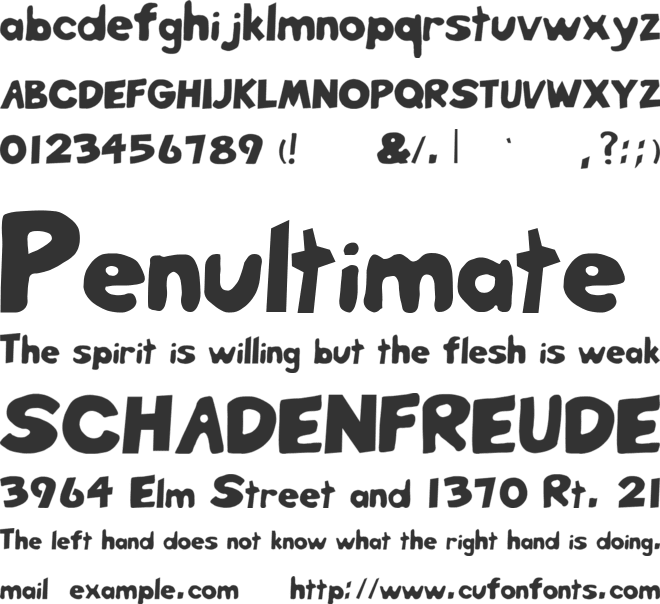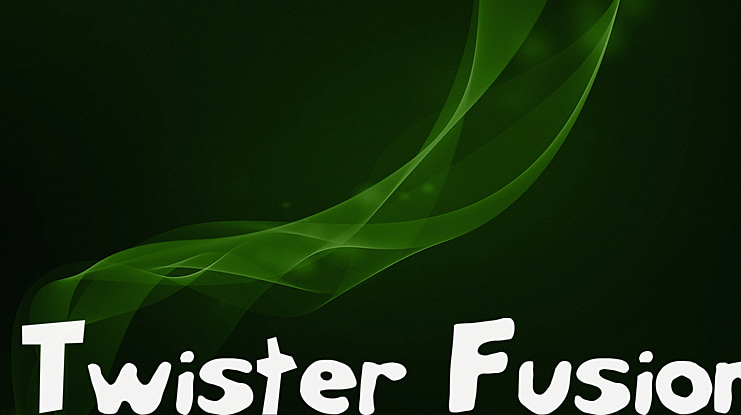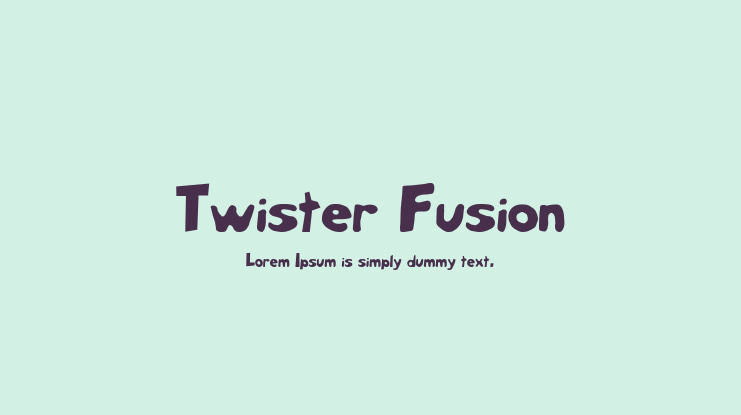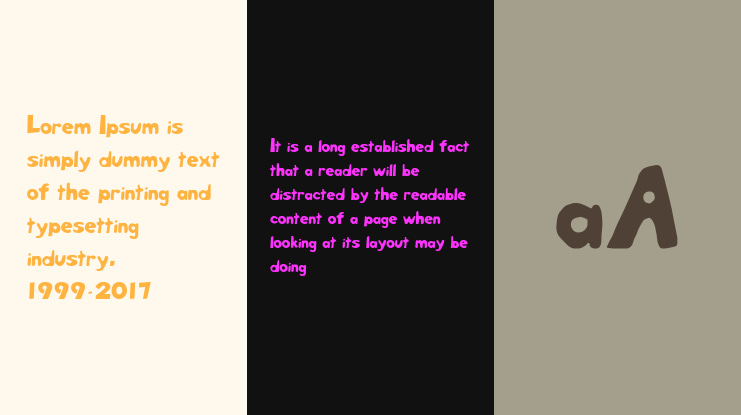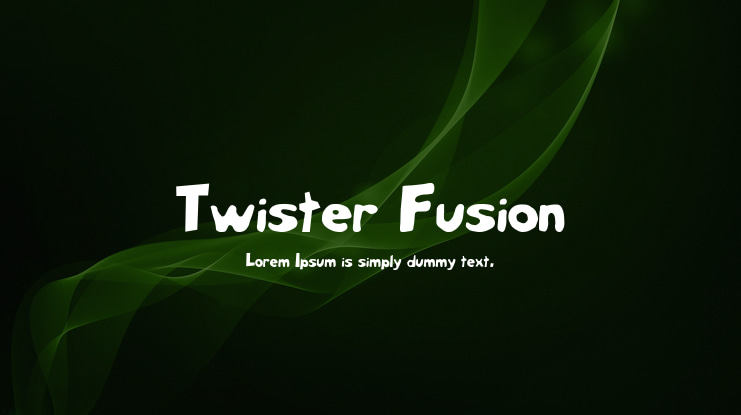
Twister Fusion Font
Cette police est une reconstitution d'une police originaire de la première sortie du jeu Astérix & Obélix XXL sur PS2 le 21 Nov. 2003: initialement encodée sous forme d'image, je l'ai redessinée et partiellement complétée. La police ne fut plus utilisée lors des sorties ultérieures sur Gamecube et PC. Les développeurs, Étranges Libellules, ont cessé leurs activités en 2012, donc n'ont pas de site internet. J'ai nommé la police "Twister Fusion", en référence à une action spécifique au jeu.